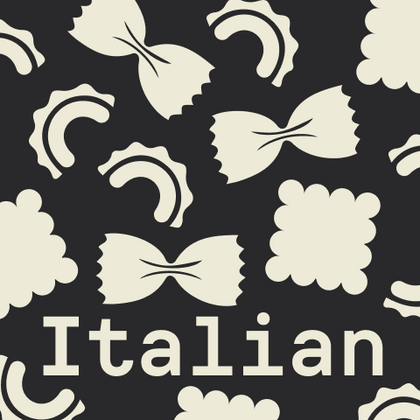
Подборка Итальянских шрифтов
Если вам нужны шрифты на итальянском языке для проектов — важно, чтобы они корректно отображали все особенности этого языка, включая акцентированные символы. В таких коллекциях, как у TypeType, вы найдете шрифт с поддержкой итальянского языка, что избавляет от проблем с отображением текста. Это удобно для дизайна меню, туристических буклетов или любых материалов, где требуется итальянская типографика. Такие гарнитуры работают без ошибок в печати и на цифровых носителях.
Выберите подходящий шрифт с поддержкой Итальянского языка. Огромная коллекция шрифтовых семейств для любых целей и задач: набор больших текстовых массивов, оформление заголовков для веб-сайтов и печатных изданий, печать на текстиле и других материалах, оформление вывесок и афиш.
Каждый из представленных шрифтов содержит Итальянский алфавит. Широкий выбор символов, знаков валют и пунктуации, шрифтовых начертаний и OpenType фич позволят применять один шрифт для разных проектов. Знаки расширенной латиницы, содержащие диакритические знаки, расширят возможности использования шрифта для разных стран.
Каждый шрифт безупречен с технической точки зрения. Многие шрифты из коллекции содержат вариативное начертание, с помощью которого можно создавать уникальное начертание для проекта.
TT Chocolates — изящный гуманистический гротеск сo сбалансированными пропорциями, близкими к классическим. Шрифт с приятным дружелюбным характером, который интуитивно воспринимается как что-то знакомое.
TT Rationalist — функциональный и оригинальный брусковый шрифт с актуальным рисунком. Он универсален и подходит как для заголовков, так и для массивов текста.
TT Commons™ Classic — универсальный геометрический гротеск для широкого круга задач.
TT Moons — узкая и контрастная антиква. Данное шрифтовое семейство очень элегантно работает в классических темах дизайна. TT Moons по стилистике относится к глиптальным новостильным шрифтам. Идеальная сфера использования TT Moons — это верстка журналов, книг и газет.
TT Disruptors — дуктальный рукописный шрифт, созданный с помощью маркера. Его рисунок уникален: потёртости, неравномерная толщина штрихов и удлинённые выносные элементы придают ему живую, динамичную текстуру и ощущение рукотворности. Характер этого шрифта своенравный и эмоциональный, но при этом тёплый и душевный.
TT Gentlemens — динамичный рукописный шрифт, в котором серьёзность и чёткость письма сочетается с элегантностью и изысканностью. У него характер и стиль настоящего джентльмена: сдержанный и всегда уместный, но при этом уверенный и эффектный.
TT Interphases Pro — неогротеск, который создавался специально для работы в интерфейсах. Среди визуальных особенностей TT Interphases Pro — плавные формы скруглений, повторяющиеся во всех элементах: благодаря им большие массивы текста читаются легко и приятно.
TT Octosquares — октагональный гротеск с футуристическим характером. Этот шрифт отличается геометричностью и своеобразной «мозаичностью»: он как бы собран из отдельных фрагментов, что проявляется и в мельчайших деталях.
TT Lakes Neue в версии 2.0 — продолжение геометрического гротеска, вдохновлённого финским функционализмом. Новая версия предоставляет больше возможностей, ведь мы не только увеличили кассовый состав и улучшили шрифт технически, но и доработали его визуальный характер.
TT Norms® Pro — один из самых востребованных шрифтов студии, выбор известных мировых брендов. Более трёх переизданий за семь лет, первые строчки на MyFonts, десятки кастомизаций. Это «рабочая лошадка», которая станет незаменимой базой любой шрифтовой коллекции.
TT Commons™ Pro — один из самых востребованных шрифтов студии. Сфера его применения практически безгранична! Беспроигрышный вариант для тех, кто ищет стильный и функциональный базовый шрифт для любых проектов.
TT Knickerbockers Grotesk символизирует собой монументальность, выраженную в как в традиционной исторической застройке Нью-Йорка, так и в его небоскрёбах. Энергия, постоянное движение и круглосуточная жизнь Нью-Йорка — все это отразилось в нашем TT Knickerbockers Script.
TT Polls берет свое начало как современный модульный брусковый шрифт. При создании шрифтового семейства TT Polls мы держали в голове его использование в дизайне на спортивную тематику, но финальная версия TT Polls отлично подходит и для более казуального дизайна и сфер применения.